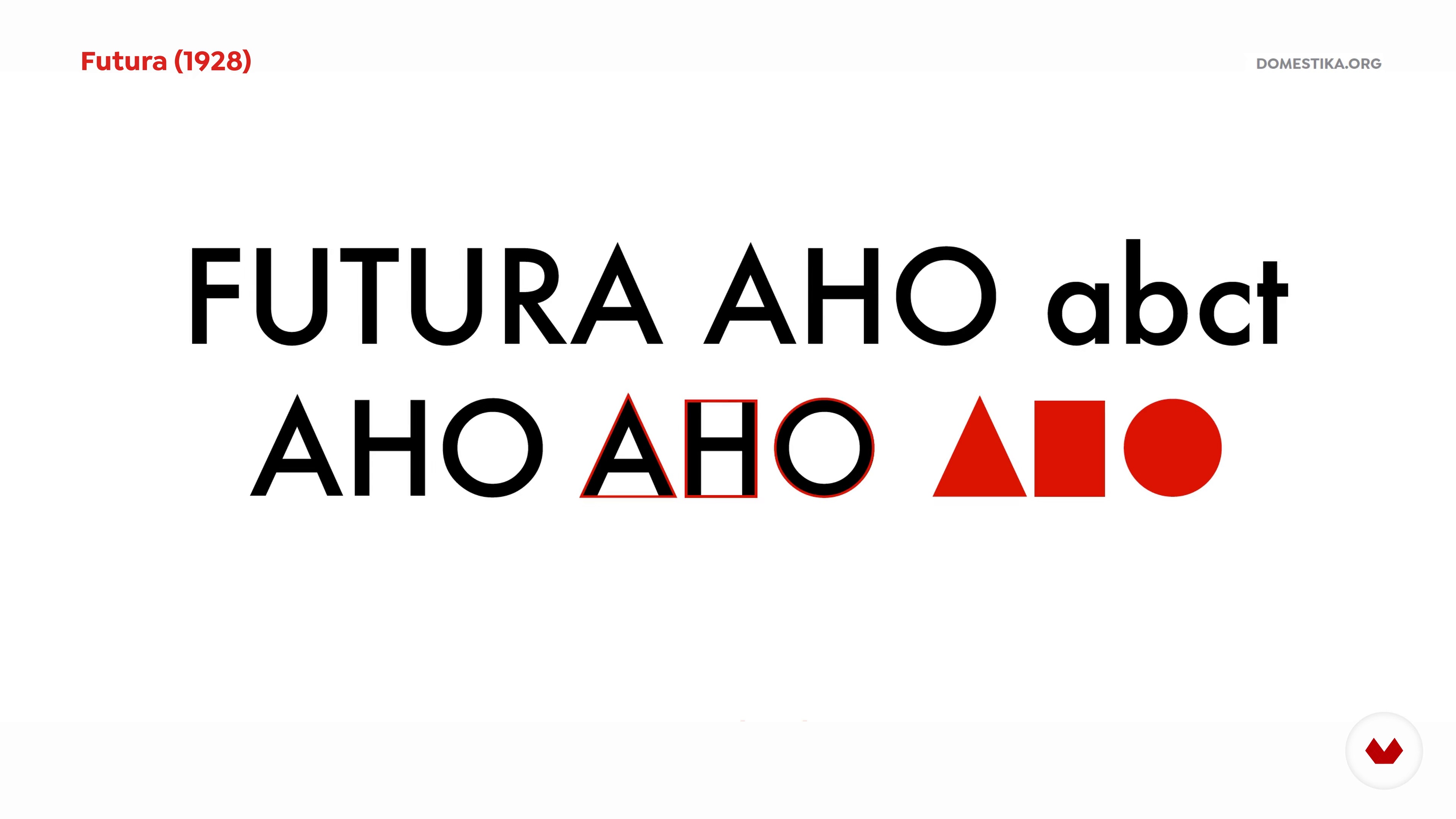
Classification typographique 1
À propos de la leçon : Classification typographique 1
“Être capable d'identifier et de classer les polices aide beaucoup à mettre de l'ordre dans la maison, donc je vais vous expliquer les caractéristiques qui définissent chaque catégorie de typographie et je donnerai un exemple pratique de la façon d'utiliser ces informations dans un projet. ”
Dans cette leçon, Álvaro Franca aborde le sujet : Classification typographique 1, qui fait partie du cours Domestika en ligne : Fondements de la typographie de A à Z. Découvrez les possibilités du choix typographique pour transmettre et renforcer votre message.
“Il y a tellement de styles de polices différents que pour naviguer dans ce monde. il est très utile de pouvoir les classer en catégories. Dans ce cours. je vais vous enseigner la manière la plus rapide et facile d'identifier une police et de décider quel rôle elle peut jouer dans votre projet. À la fin. je vais démontrer comment l'histoire et la classification de la typographie peuvent influencer une pièce de design. en créant une couverture de livre 100% typographique. Voyons cela. La classification typographique est le système que nous avons pour diviser le vaste monde des typographies ex...”